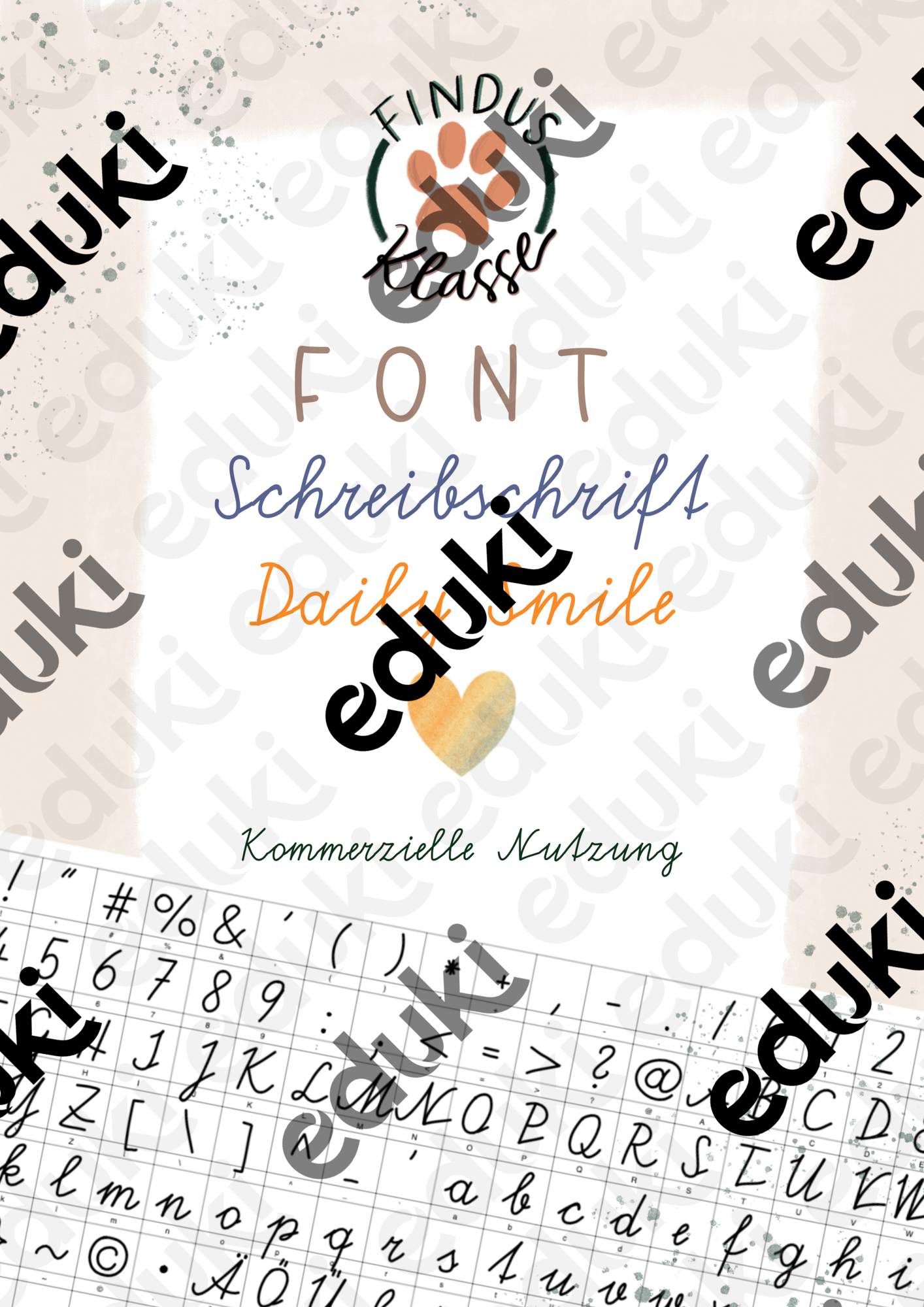
Mit DAILY SMILE, einer Schreibschrift (Österreich) kannst du wunderbar Arbeitsblätter gestalten. Eine kommerziell nutzbare Schreibschrift für den Bildungsbereich!
Font Findusklasse Daily Smile Schreibschrift